ถ้าคุณเคยมีอาการฮัมเพลงออกมาโดยไม่รู้ตัว หรือมีเมโลดี้กำลังบรรเลงอยู่ในหัว และเพลงนั้นเรายังไม่ทันได้รู้จักชื่อด้วยซ้ำ อาการแบบนี้มีคำเฉพาะเรียกว่า Earworm มันเกิดขึ้นในบางเพลง เช่นเพลง SUPER วาเลนไทน์ ที่กำลังเป็นกระแสในตอนนี้ นอกจากติดหูแล้วก็ยังติดตาอีกด้วย เจน นุ่น โบว์ กันทั้งวัน
เราคิดว่าฟอนต์ก็คงไม่ต่างกัน เราเข้าไปหา Reference ใน Pinterest เวลาต้องทำ Artwork สักชิ้น เราจะเจอกับสไตล์ต่าง ๆ โดยเฉพาะงานโปสเตอร์เราพบว่าส่วนใหญ่เลือกใช้ Typo ที่มีความแข็ง ฟอนต์ตรงอ่านง่าย สร้างภาพจำให้เราเวลาต้องออกแบบงานสักชิ้น หลายคนอาจเริ่มต้นงานด้วยการวางฟอนต์ง่าย ๆ ก่อนเริ่มปรับมันจนจบ หรือบางครั้งจบงานตั้งแต่ดราฟแรกด้วยฟอนต์ง่าย ๆ ได้เช่นกัน
5 Font ฟรีที่เราหยิบขึ้นมาแนะนำ จากเว็บ DaFont เว็บที่เข้าไปหาฟอนต์ฟรีได้ง่าย ๆ เช่นกัน
Bebas Neue
Gobold
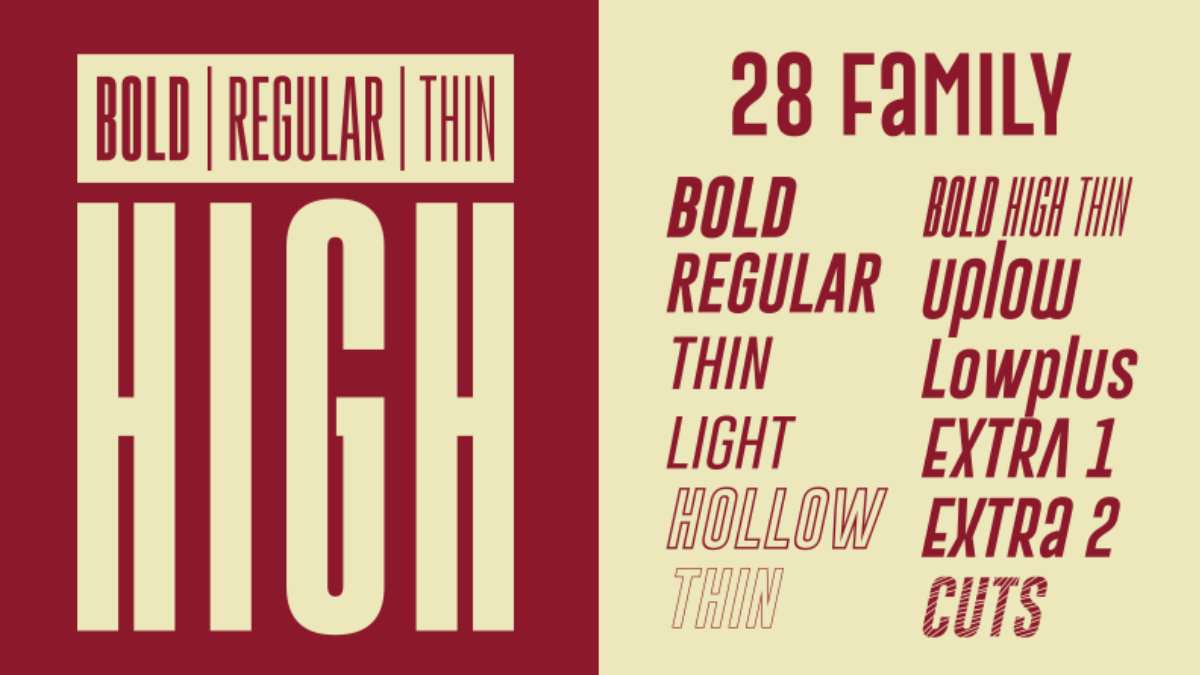
Keep Calm
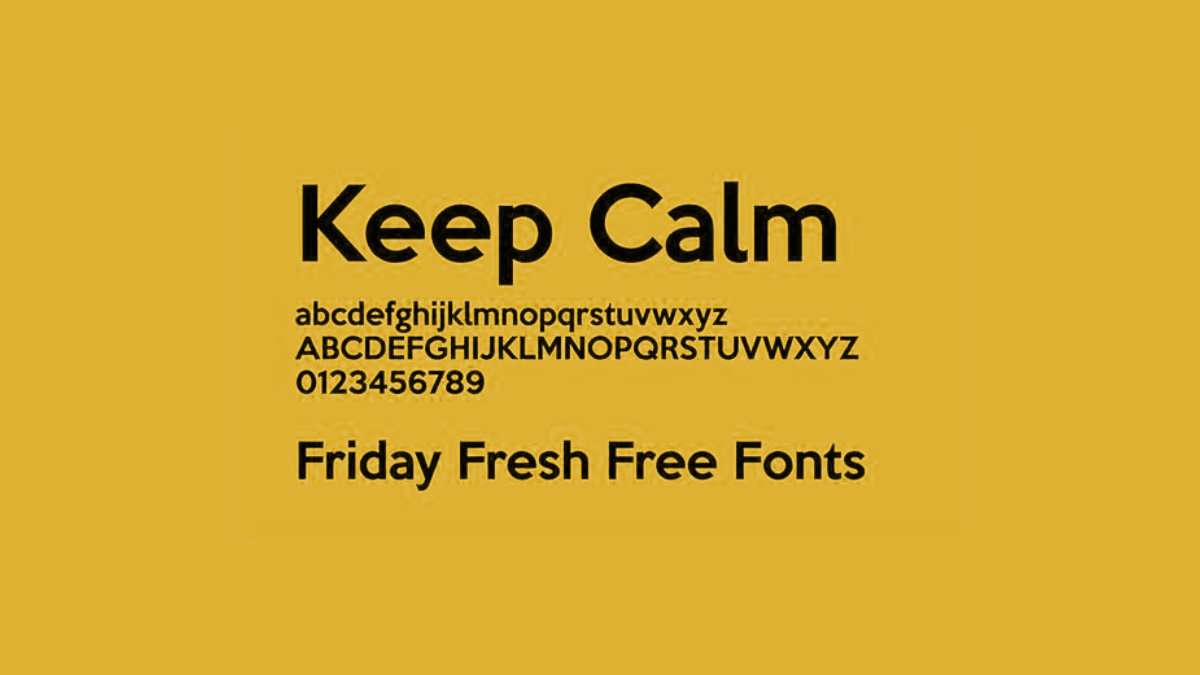
MADE Tommy
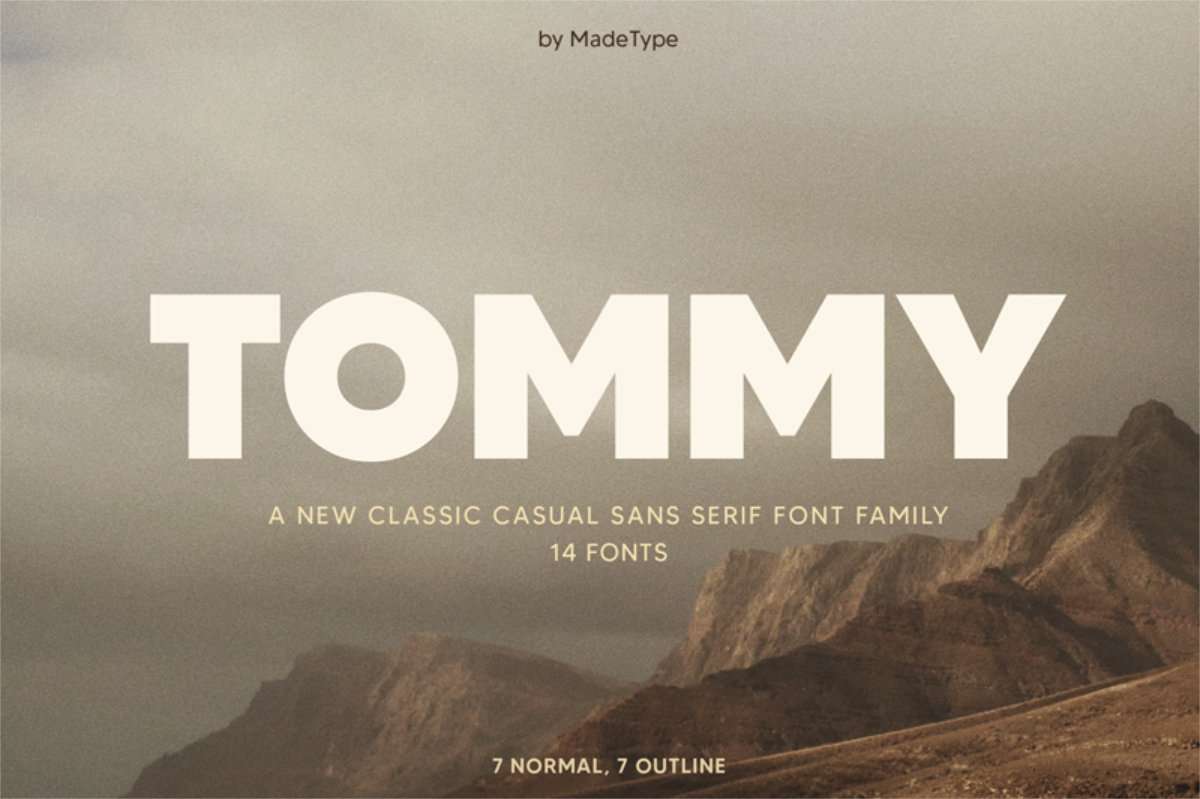
Mont
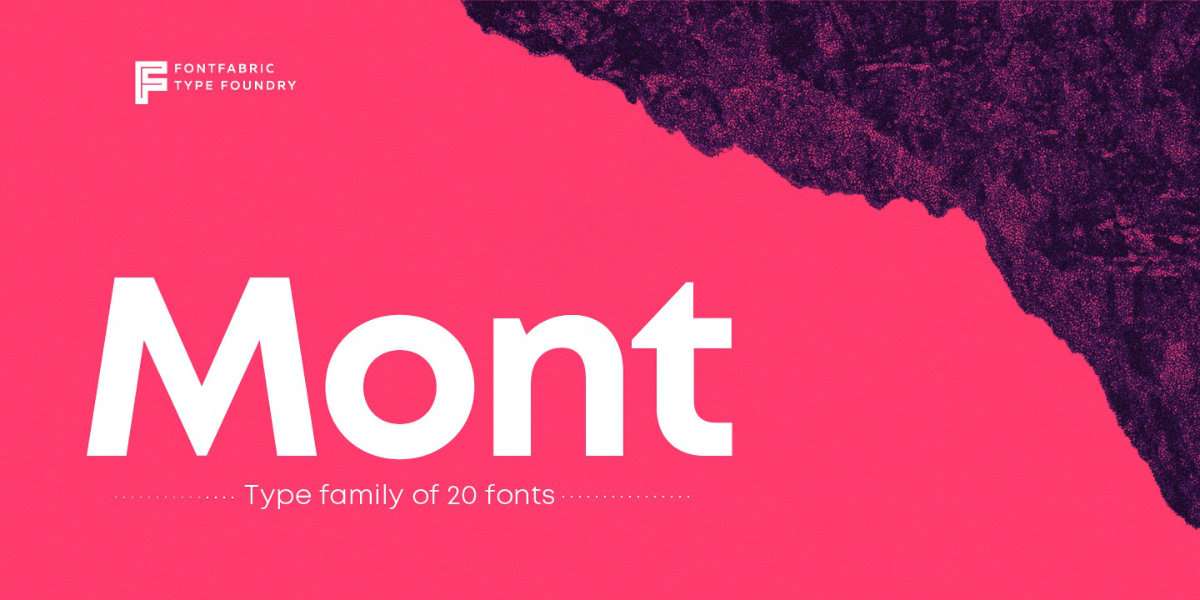
นอกเหนือจาก Brief ที่ได้รับ การเข้าใจลูกค้าและการเข้าใจตัวเอง การที่เราหาจุดตรงกลางได้เจอมันอาจจะเป็นหนทางสู่การจบงานที่ไวและดีที่สุด หวังว่าบทความนี้จะเป็นประโยชน์ของใครไม่มากก็น้อย